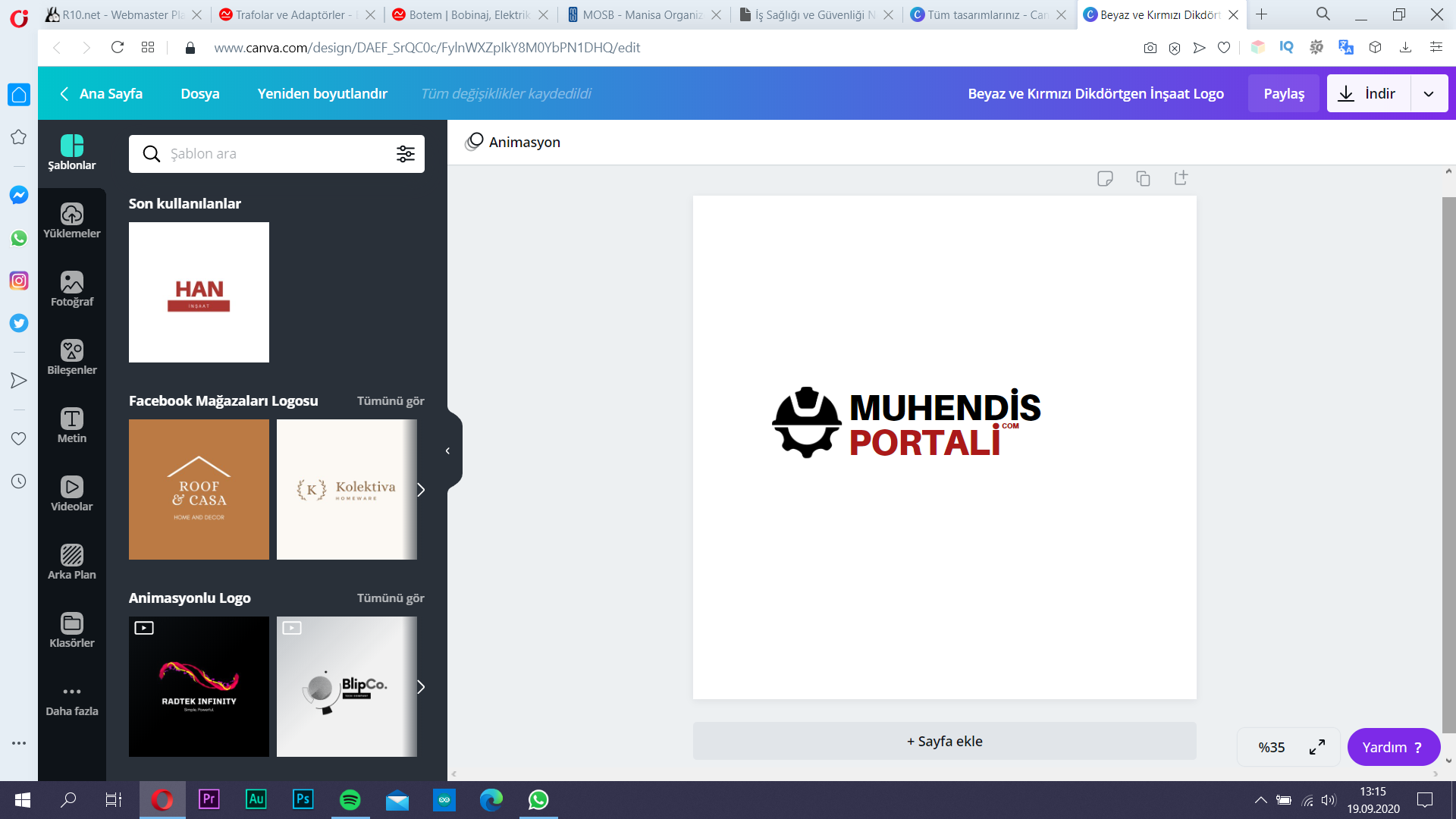
Logo için font önerisi arıyorum
- 19-09-2020, 13:16:20Merhabalar öğrenci olduğum için web sitemin logosunu kendim tasarlıyorum kabaca böyle bir tasarım çıkardım. Fontlar çok sade geldi önerdiğiniz uyum içerisinde olan fontlar varsa yardımcı olur musunuz?
- 19-09-2020, 13:20:29Denedim poppins baya benziyor bana biraz daha farklı bir font lazım proximada çıkmıyorkaraoglan01 adlı üyeden alıntı: mesajı görüntüle